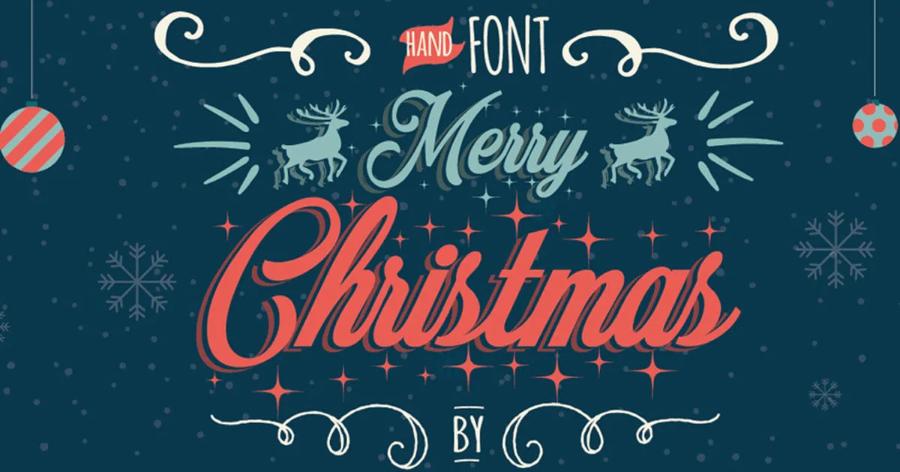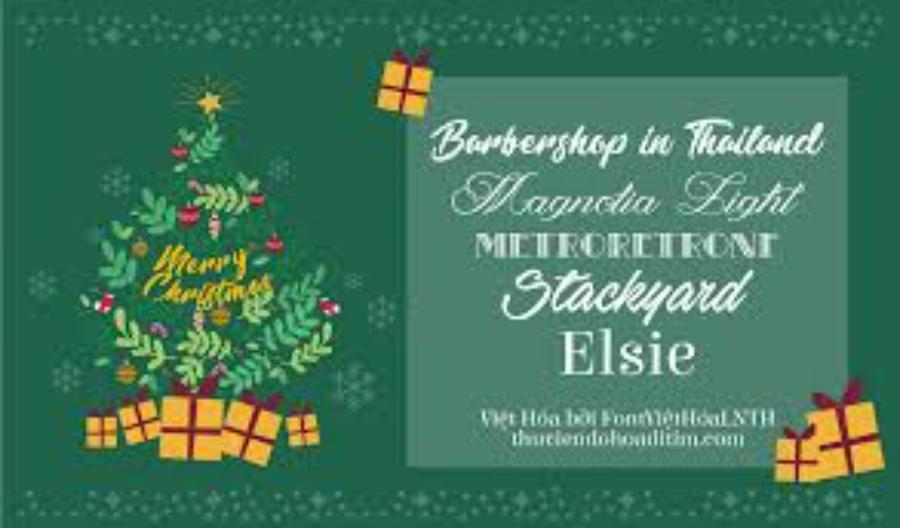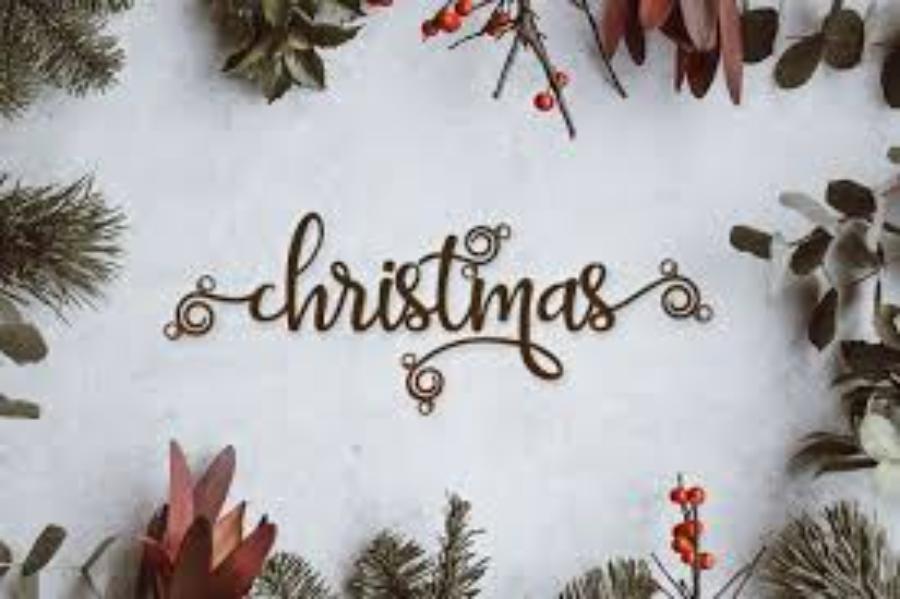
Những Font Chữ Việt Hóa Mùa Giáng Sinh Cực Nghệ: Thổi Hồn Noel Vào Thiết Kế Của Bạn
Mùa Giáng sinh không chỉ là thời gian của ánh đèn lấp lánh và những bài hát rộn ràng, mà còn là dịp để thể hiện tính sáng tạo trong thiết kế. Việc lựa chọn font chữ Việt hóa phù hợp sẽ giúp các thiết kế mang tinh thần Giáng sinh đầy nghệ thuật và ấn tượng hơn.
Mùa Giáng Sinh, mùa của những điều kỳ diệu, của sự ấm áp và sẻ chia, đang đến gần. Không chỉ không gian xung quanh được trang hoàng lộng lẫy, mà ngay cả những thiết kế, ấn phẩm truyền thông cũng cần mang đậm hơi thở của Noel. Một trong những yếu tố quan trọng tạo nên sự khác biệt và thu hút chính là việc lựa chọn font chữ. Bài viết này, Sadesign sẽ đưa bạn khám phá thế giới của những font chữ Việt hóa mùa Giáng Sinh cực nghệ, giúp bạn thổi hồn không khí Noel vào mọi dự án thiết kế.
1. Tại Sao Font Chữ Việt Hóa Lại Quan Trọng Trong Thiết Kế Giáng Sinh?
Trước khi đi vào chi tiết các font chữ, hãy cùng nhau làm rõ tầm quan trọng của font chữ Việt hóa trong bối cảnh thiết kế mùa Giáng Sinh:
• Truyền tải trọn vẹn thông điệp: Font chữ không chỉ đơn thuần là các ký tự, mà còn mang trong mình cảm xúc và phong cách riêng. Một font chữ phù hợp sẽ giúp truyền tải thông điệp Giáng Sinh một cách trọn vẹn và hiệu quả nhất, từ sự ấm áp, vui tươi đến vẻ trang trọng, cổ điển.
• Tăng tính thẩm mỹ và độc đáo: Những font chữ được thiết kế riêng cho mùa Giáng Sinh thường mang những họa tiết, đường nét đặc trưng như hình cây thông, bông tuyết, chuông reo, hay phong cách viết tay ấm áp. Việc sử dụng chúng sẽ giúp thiết kế của bạn trở nên độc đáo, ấn tượng và đậm chất Noel hơn.
• Gần gũi và dễ đọc đối với người Việt: Font chữ Việt hóa đảm bảo hiển thị đầy đủ các dấu tiếng Việt, giúp người đọc dễ dàng tiếp nhận thông tin mà không gặp bất kỳ trở ngại nào. Điều này đặc biệt quan trọng trong các ấn phẩm hướng đến đối tượng người Việt.
• Thể hiện sự chuyên nghiệp và đầu tư: Việc lựa chọn và sử dụng font chữ Việt hóa đẹp mắt cho thấy sự chuyên nghiệp và đầu tư kỹ lưỡng của bạn vào từng chi tiết của thiết kế.
• Tạo sự kết nối cảm xúc: Một font chữ mang đậm không khí Giáng Sinh có thể gợi nhớ những kỷ niệm đẹp, tạo cảm giác ấm áp, háo hức và kết nối cảm xúc với người xem.
2. Phân Loại Các Font Chữ Việt Hóa Mùa Giáng Sinh Cực Nghệ
Để giúp bạn dễ dàng lựa chọn, chúng ta có thể phân loại các font chữ Việt hóa mùa Giáng Sinh thành một số nhóm chính sau:
2.1. Font Chữ Script (Viết Tay) Mang Hơi Thở Ấm Áp
Đây là nhóm font chữ được ưa chuộng nhất trong các thiết kế Giáng Sinh bởi vẻ đẹp mềm mại, uyển chuyển và cảm giác ấm áp, thân mật mà nó mang lại.
• Đặc điểm: Các nét chữ thường được kết nối liền mạch, có độ dày mỏng khác nhau, tạo cảm giác như chữ viết tay tự nhiên. Một số font còn được thêm vào các chi tiết trang trí nhẹ nhàng như dấu móc cách điệu, đường cong mềm mại.
• Ứng dụng: Phù hợp cho thiệp mời, lời chúc, tiêu đề thư, chữ ký, các thiết kế mang phong cách vintage, rustic hoặc handmade.
• Ví dụ:
• Christmas Wish: Một font script thanh lịch với những đường cong duyên dáng, tạo cảm giác nhẹ nhàng và tinh tế.
• Winter Calligraphy: Font chữ viết tay đậm nét, mạnh mẽ nhưng vẫn giữ được sự ấm áp và gần gũi.
• Holiday Script: Font chữ vui tươi, trẻ trung với những nét chữ tròn trịa, phù hợp cho các thiết kế năng động.
• Snowflake Script: Font script được trang trí thêm các họa tiết bông tuyết nhỏ xinh, tăng thêm không khí Noel.
• Cozy Winter: Một font chữ mềm mại, tròn trịa, gợi cảm giác ấm cúng và thư giãn.
2.2. Font Chữ Serif (Có Chân) Cổ Điển và Trang Trọng
Nhóm font chữ serif mang đến vẻ đẹp cổ điển, trang trọng và lịch sự, thường được sử dụng trong các thiết kế mang tính truyền thống của mùa Giáng Sinh.
• Đặc điểm: Các chữ cái có thêm các nét nhỏ ở cuối các nét chính (chân chữ). Font serif thường tạo cảm giác ổn định, đáng tin cậy và trang trọng.
• Ứng dụng: Phù hợp cho tiêu đề lớn, các đoạn văn bản trang trọng, thiệp mời cao cấp, banner quảng cáo mang phong cách cổ điển.
• Ví dụ:
• Christmas Carol: Một font serif thanh lịch với các nét chữ tinh tế, gợi nhớ đến những bản thánh ca Giáng Sinh.
• Noel Classic: Font serif đậm nét, mạnh mẽ, tạo cảm giác vững chãi và truyền thống.
• Winterfell: Một font serif cách điệu với các đường nét độc đáo, mang hơi hướng cổ tích mùa đông.
• Santa's Sleigh: Font serif được thiết kế với các chi tiết uốn lượn nhẹ nhàng, gợi hình ảnh chiếc xe trượt tuyết của ông già Noel.
• Evergreen: Một font serif đơn giản nhưng tinh tế, mang đến cảm giác tươi mới và bền vững như cây thông Noel.
2.3. Font Chữ Sans-Serif (Không Chân) Hiện Đại và Tối Giản
Nhóm font chữ sans-serif mang đến vẻ đẹp hiện đại, tối giản và dễ đọc, phù hợp cho các thiết kế Giáng Sinh theo phong cách đương đại.
• Đặc điểm: Các chữ cái không có chân, đường nét rõ ràng, mạch lạc. Font sans-serif thường tạo cảm giác trẻ trung, năng động và hiện đại.
6. Tổng Kết
Những font chữ Việt hóa mùa Giáng Sinh cực nghệ là một công cụ mạnh mẽ giúp bạn truyền tải trọn vẹn tinh thần Noel vào các thiết kế của mình. Việc lựa chọn và sử dụng font chữ phù hợp không chỉ tăng tính thẩm mỹ, độc đáo mà còn tạo sự kết nối cảm xúc với người xem. Hy vọng với những thông tin chi tiết và gợi ý trong bài viết này, bạn sẽ tìm được những font chữ ưng ý và tạo ra những thiết kế Giáng Sinh thật ấn tượng và đáng nhớ. Chúc bạn một mùa Giáng Sinh an lành và tràn đầy sáng tạo!